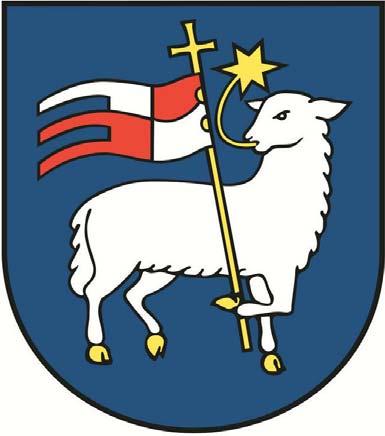
2 DIZJNMNUÁL mesta Trenčín sa skladá z piatich častí (, B, C, D, E ) definuje podobu a pravidlá používania základných častí vizuálneho štýlu mesta, ako logo a erb sú skonštruované tak, aby tvorili samostatné segmenty, a zároveň farebne, proporčne harmonický celok nápis v logotype a erbe je identický a umožňuje toto prepojenie doplnkovou vrstvou vizuálneho štýlu sú štruktúry Samostatné použitie loga ( v ďalšom aplikácia»logo«): plikácia»logo«je povolená pri všetkých ostatných príležitostiach, včítane: dokumentov tlačovín a iných písomných výstupov Mesta Trenčín a Mestského úradu v Trenčíne smerom navonok (externá komunikácia s klientom), dokumentov tlačovín a iných písomných výstupov Mesta Trenčín a Mestského úradu v Trenčíne smerom dovnútra (interná komunikácia v rámci organizačnej štruktúry Mesta Trenčín), označenia hnuteľného majetku (autá, prostriedky hromadnej dopravy, inventár a pod.), prípadne iného majetku Mesta Trenčín, ktorý je možné využiť ako nosič pre vizuálnu komunikáciu mesta smerom navonok, ZNKY I. LOGO 2. ERB ZNKY reklamných a propagačných výstupov, výstupov v oblasti kultúry, cestovného ruchu a iných výstupov Mesta Trenčín smerujúcich k propagácii mesta Trenčín, reklamných a propagačných výstupov, výstupov v oblasti kultúry, cestovného ruchu a iných výstupov smerujúcich k propagácii mesta Trenčín realizovaných inými spolupracujúcimi subjektami, pričom v tomto prípade podlieha použitie loga súhlasu Mestského úradu v Trenčíne v zmysle Čl.2, ods.2 tohoto VZN. DIZJNMNUÁL ~ MESTO TRENČÍN 2005 ~ 2006
3 X Y X 1. LOGO 1.1. ZNK konštrukcia geometria LOGOTYP je znak a nápis 4X=Y Y Y Y Y 3,5X 3,5X 4,5X ZNK je zložený z niekoľkých častí, konkrétne zo štvrťkruhu, štvrťkružníc a štvorca. časti sú zkonštruované pomocou štvorcovej siete 16x16(X) a kružníc s polomerom 4X, a 8X tieto základné súčiastky sú ďalej upravené pomocou rovnakej siete - duktus modrej vlny sa mení zo 4X na 3X, - duktus žltej vlny zo 4X na 4,5X z takto tvarovo upravených segmentov je zkonštruovaný znaklogo mesta Trenčín 1.1. ZNK konštrukcia geometria ZNKY I. LOGO DIZJNMNUÁL ~ MESTO TRENČÍN 2005 ~ 2006
4 sieť grid štvorcová sieť 16x16(X) je otočená o 45 a rozvinutá/zväčšená o 4X na každej strane jednotlivé segmenty loga sú otočené taktiež o 45 rozmiestnenie častí do podoby znaku/loga je rovnako definované sieťou, vzdialenosť zeleného štvorca a modrej a žltej vlny je 1X umiestnenie červeného štvrťkruhu je na rovnakej osi ako modrá vlna pomocou tejto siete, segmentov a ich vzájomných vzťahov môžme zkonštruovať logo bez digitálneho podkladu 1.1. ZNK sieť ZNKY I. LOGO DIZJNMNUÁL ~ MESTO TRENČÍN 2005 ~ 2006
5 TRENČÍN ŽLTÁ PNTONE: 116C CMYK: C000 M014 Y100 K000 RGB: R254 G209 B farby loga cmyk, pantone, čb, mono vzorkovník farieb farby loga a erbu sú zjednotené v nasledujúcich farbách TRENČÍN MODRÁ PNTONE: CYN CMYK: C100 M000 Y000 K000 RGB: R000 G159 B218 TRENČÍN ČERVENÁ PNTONE: 485C CMYK: C000 M096 Y100 K000 RGB: R213 G043 B030 TRENČÍN ZELENÁ PNTONE: 376C CMYK: C059 M000 Y100 K000 RGB: R122 G184 B000 TRENČÍN ČIERN PNTONE: BLCK C CMYK: C030 M030 Y030 K100 RGB: R000 G000 B000 TRENČÍN SIVÁ PNTONE: COOL GRY 50% 7C CMYK: C020 M015 Y011 K040 RGB: R154 G155 B farby loga 1.1. ZNK ZNKY I. LOGO DIZJNMNUÁL ~ MESTO TRENČÍN 2005 ~ 2006
6 vzorkovník farieb ZNKY I. LOGO DIZJNMNUÁL ~ MESTO TRENČÍN 2005 ~ ZNK vzorkovník farieb TRENČÍN ŽLTÁ PNTONE: 116C CMYK: C000 M014 Y 100 K000 RGB: R 254 G209 B000 TRENČÍN ŽLTÁ PNTONE: 116C CMYK: C000 M014 Y 100 K000 RGB: R 254 G209 B000 TRENČÍN ŽLTÁ PNTONE: 116C CMYK: C000 M014 Y 100 K000 RGB: R 254 G209 B000 TRENČÍN MODRÁ PNTONE: CYN CMYK: C 100 M000 Y000 K000 RGB: R000 G159 B218 TRENČÍN MODRÁ PNTONE: CYN CMYK: C 100 M000 Y000 K000 RGB: R000 G159 B218 TRENČÍN MODRÁ PNTONE: CYN CMYK: C 100 M000 Y000 K000 RGB: R000 G159 B218 TRENČÍN ČERVENÁ PNTONE: 485C CMYK: C000 M096 Y 100 K000 RGB: R 213 G043 B030 TRENČÍN ČERVENÁ PNTONE: 485C CMYK: C000 M096 Y 100 K000 RGB: R 213 G043 B030 TRENČÍN ČERVENÁ PNTONE: 485C CMYK: C000 M096 Y 100 K000 RGB: R 213 G043 B030 TRENČÍN ZELENÁ PNTONE: 376C CMYK: C059 M000 Y 100 K000 RGB: R 122 G184 B000 TRENČÍN ZELENÁ PNTONE: 376C CMYK: C059 M000 Y 100 K000 RGB: R 122 G184 B000 TRENČÍN ZELENÁ PNTONE: 376C CMYK: C059 M000 Y 100 K000 RGB: R 122 G184 B000 TRENČÍN ČIERN PNTONE: BLCK C CMYK: C030 M030 Y030 K100 RGB: R000 G000 B000 TRENČÍN SIVÁ PNTONE: COOL GRY 7C CMYK: C020 M015 Y011 K040 RGB: R154 G155 B156 TRENČÍN SIVÁ PNTONE: COOL GRY 7C CMYK: C020 M015 Y011 K040 RGB: R154 G155 B156 TRENČÍN SIVÁ PNTONE: COOL GRY 7C CMYK: C020 M015 Y011 K040 RGB: R154 G155 B156
7 48X ochranná zóna a) blok 36X 6X 2X 6X v nasledujúcej štvorcovej sieti je definovaná kompozícia znaku, nápisu a bloku, vo variante (blok) v plnofarebnej variante na bielom 6X (neutrálnom pozadí) tento blok definuje ochrannú zónu ochranná zóna je priestor do ktorého nesmie zasahovať iný vizuálny prvok, zmyslom OZ je zachovať čitateľnosť značky minimalna ochranná zóna je 2X OZ vychádza z konštrukcie a proporcií loga optimálna ochranná zóna je 6X (1/6 šírky bloku značky) 1.1. ZNK ochranná zóna a) blok ZNKY I. LOGO DIZJNMNUÁL ~ MESTO TRENČÍN 2005 ~ 2006
8 ochranná zóna b) stred v nasledujúcej štvorcovej sieti je definovaná kompozícia znaku, nápisu a bloku, vo variante B (stred) v plnofarebnej variante na bielom 6X (neutrálnom pozadí) tento blok definuje ochrannú zónu ochranná zóna je priestor do ktorého nesmie zasahovať iný vizuálny prvok, zmyslom OZ je zachovať čitateľnosť značky minimalna ochranná zóna je 2X OZ vychádza z konštrukcie a proporcií loga optimálna ochranná zóna je 6X (1/6 šírky bloku značky) 1.1. ZNK ochranná zóna b) stred ZNKY I. LOGO DIZJNMNUÁL ~ MESTO TRENČÍN 2005 ~ 2006
9 ZNKY I. LOGO DIZJNMNUÁL ~ MESTO TRENČÍN 2005 ~ ZNK ochranná zóna c) riadok 6X ochranná zóna c) riadok v nasledujúcej štvorcovej sieti je definovaná kompozícia znaku, nápisu a bloku vo variante C (riadok) optimálna ochranná zóna je 6X (1/6 šírky bloku značky)
10 tri typi loga a) blok b) stred c) riadok podľa uvedených typov loga môžme vidieť dominanciu znaku (a), alebo typografie (c), prípadne ich a) blok b) stred c) riadok pravý, riadok ľavý vyváženosť (b) a) blok b) stred c) riadok plnofarebná CMYK varianta červenobiela varianta tri typi loga a) blok b) stred c) riadok ZNKY I. LOGO DIZJNMNUÁL ~ MESTO TRENČÍN 2005 ~ 2006
11 tri typi loga a) blok b) stred c) riadok ZNKY I. LOGO DIZJNMNUÁL ~ MESTO TRENČÍN 2005 ~ tri typi loga a) blok b) stred c) riadok pravý, riadok stred logo z nápisom MESTO TRENČÍN logo z nápisom CITY OF TRENČÍN a) blok b) stred c) riadok plnofarebná CMYK varianta červenobiela varianta